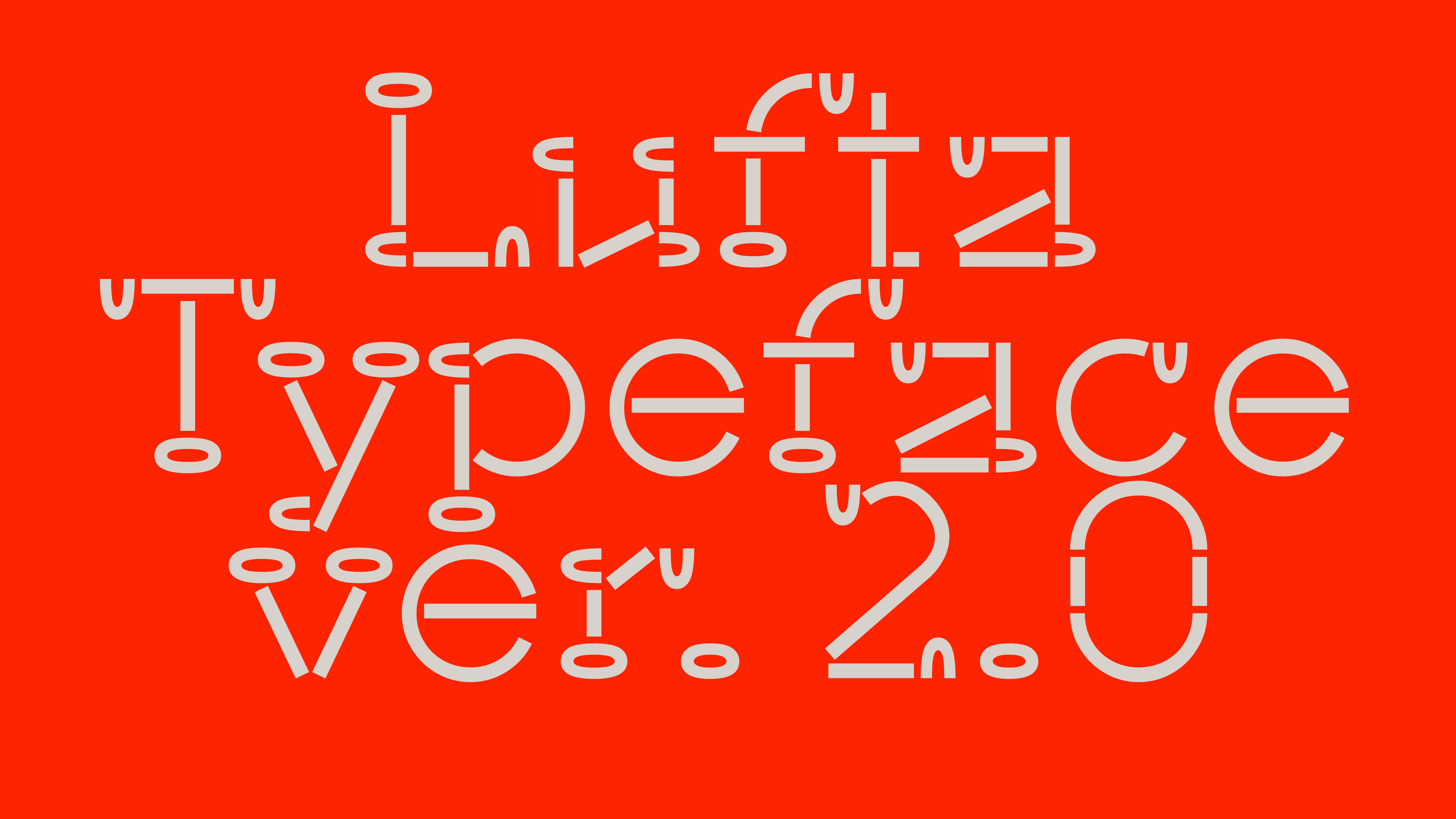
Время от времени дизайнер Владимир Коломейцев присылает в телеграм-чат Playfaces надпись и предлагает участникам сделать леттеринг на её основе. С одной из таких надписей и начался шрифт Lufta. Унаследовав от прототипа только необычную форму засечек, он превратился в дружелюбную и почти трафаретную брусковую антикву, которая будет одинаково хорошо работать и на светоотражающих патчах для одежды, и в айдентике deep-tech стартапа, и в DIY-проектах (например, навигации по гаражной распродаже).
Надпись из чата Playfaces. Один из вариантов логотипа для бара «Игла». Дизайн: Владимир Коломейцев, Андрей Абрамов (KOBRA). Задание: посмотреть на засечку как на самостоятельный графический элемент.
В Lufta — три начертания: технологичное Normal, тёплое Rounded и напоминающее типографику музыкальных
Lufta — шрифт Арины Шокаревой, независимой дизайнерки, живущей и работающей в Сербии.